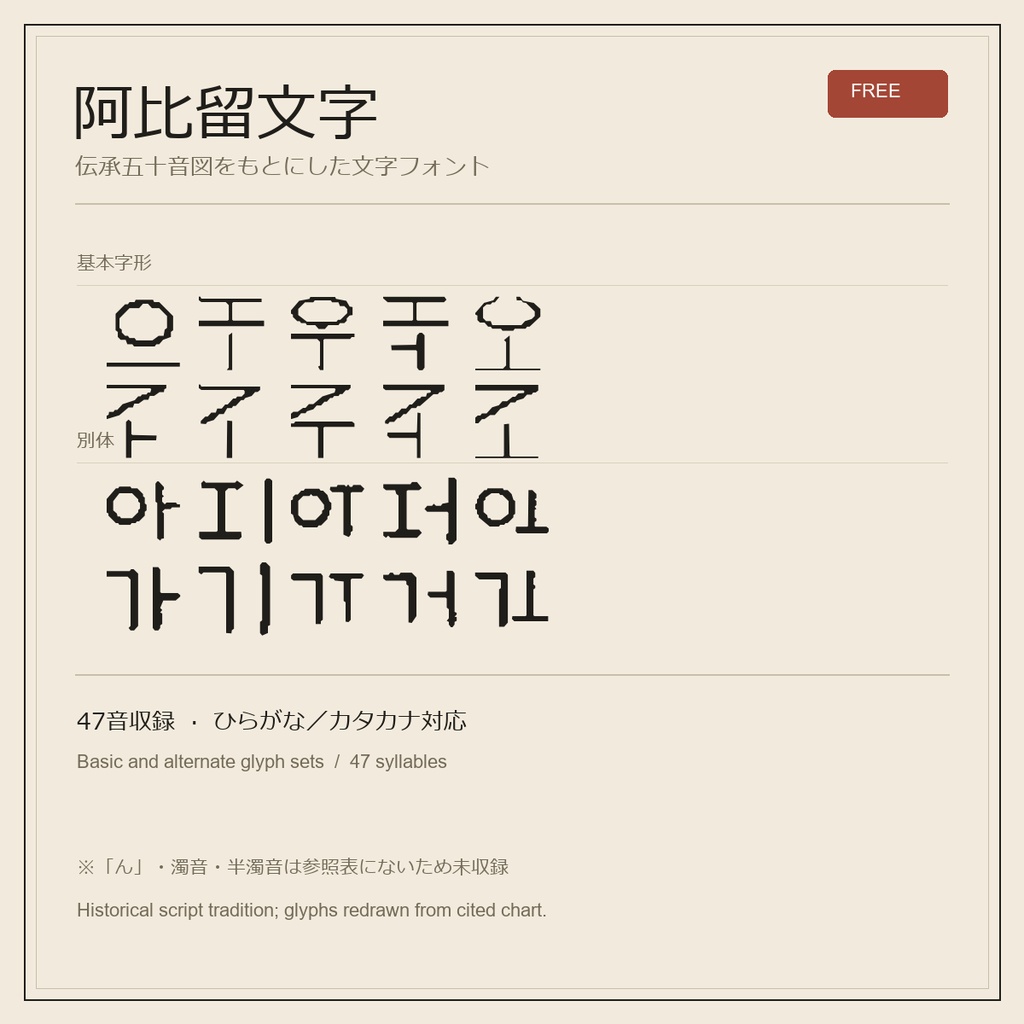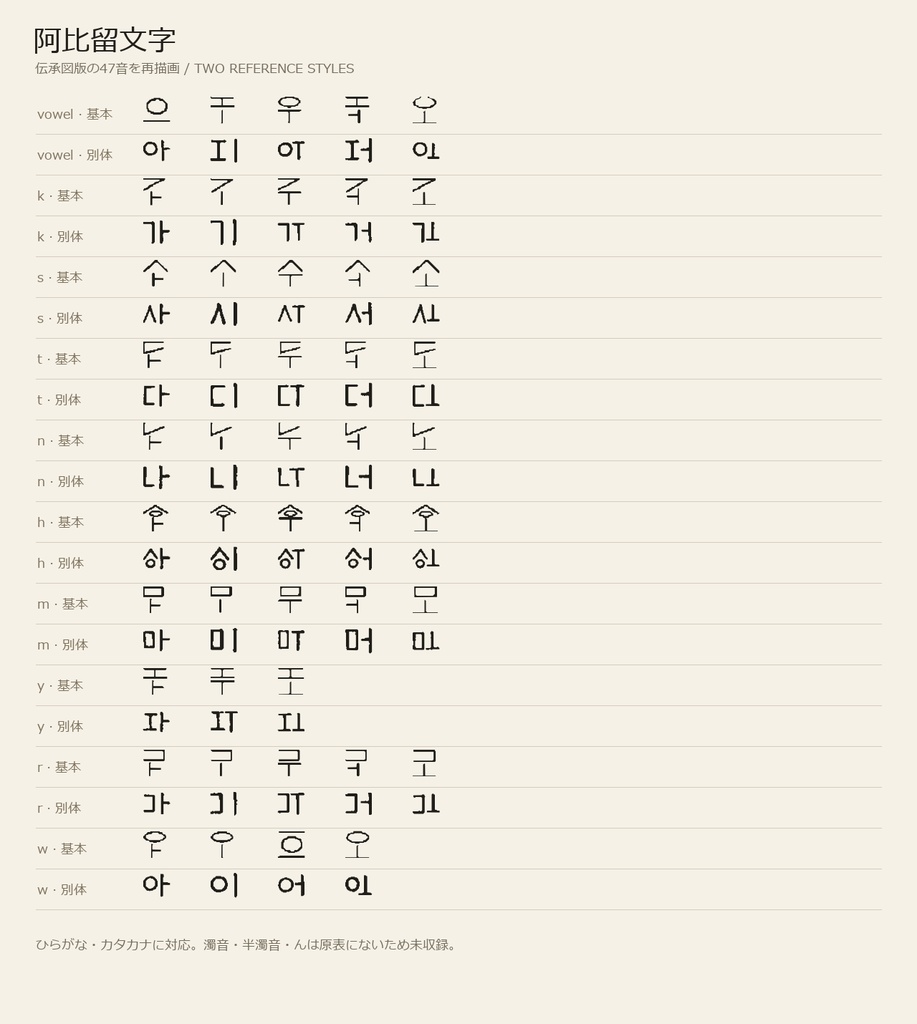
阿比留文字フォント|基本字形・別体【無料】
阿比留文字の伝承五十音図をもとに字形を再描画した、無料のかなフォントです。 ■ 収録内容 ・基本字形47音、別体47音の2種類 ・ひらがな、カタカナの47音に対応 ・ひらがなとカタカナは同じ記号になります ■ 収録外 参照表にない「ん」・濁音・半濁音・小書きかなは収録していません。 ■ ファイル形式 TTFフォント2種、見本画像、READMEをZIPに収録。 ■ 出典と注意 公開されている阿比留文字一覧を参照して字形を再描画しています。歴史上の文字体系の実在や学術的校訂を示すものではありません。 出典元の掲載字形に由来するため、商用利用の条件は出典元へご確認ください。 出典: https://miko.org/~uraki/kuon/furu/text/sindaimonji/ahiru01/ahiru_list.htm